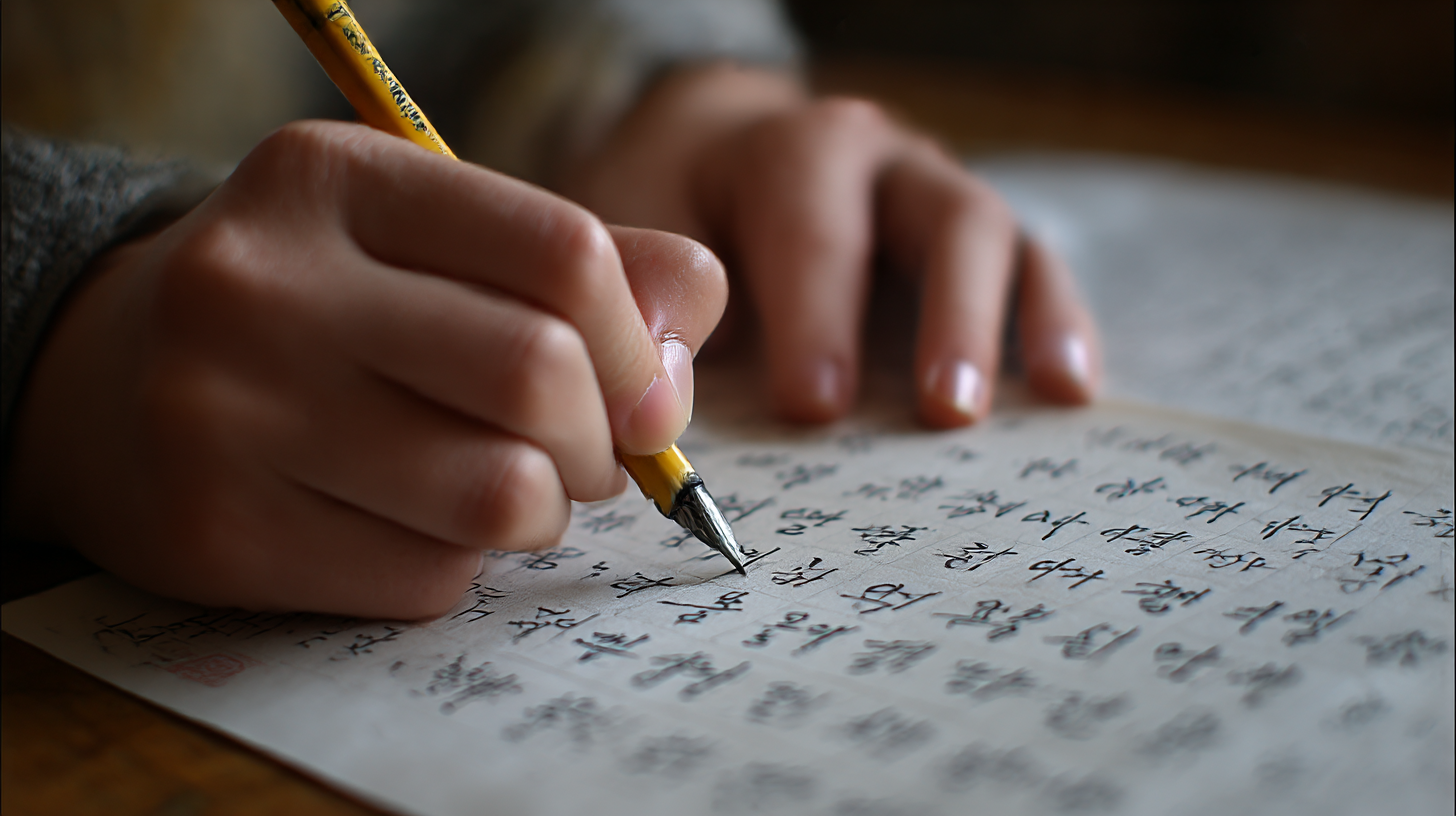
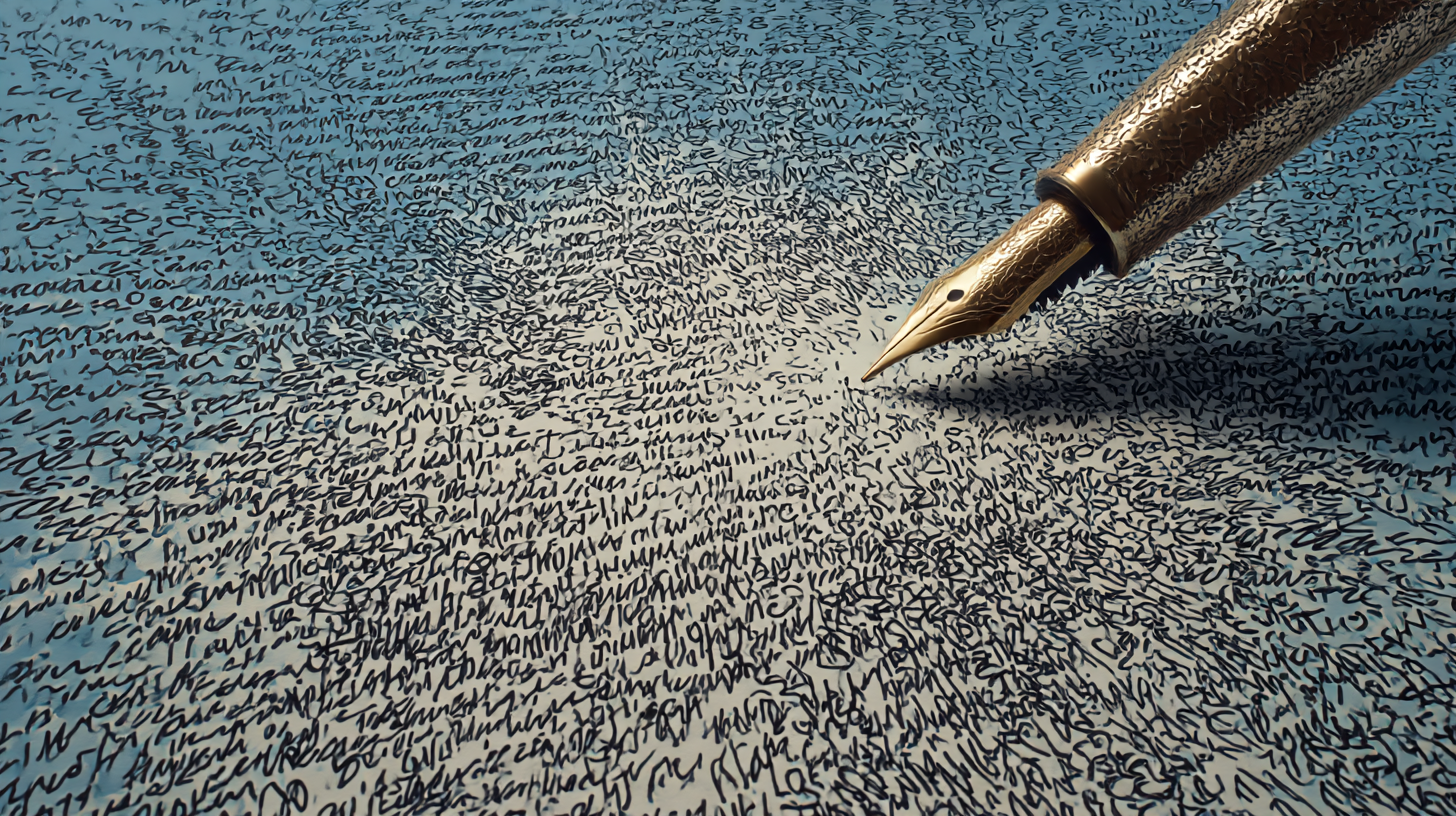
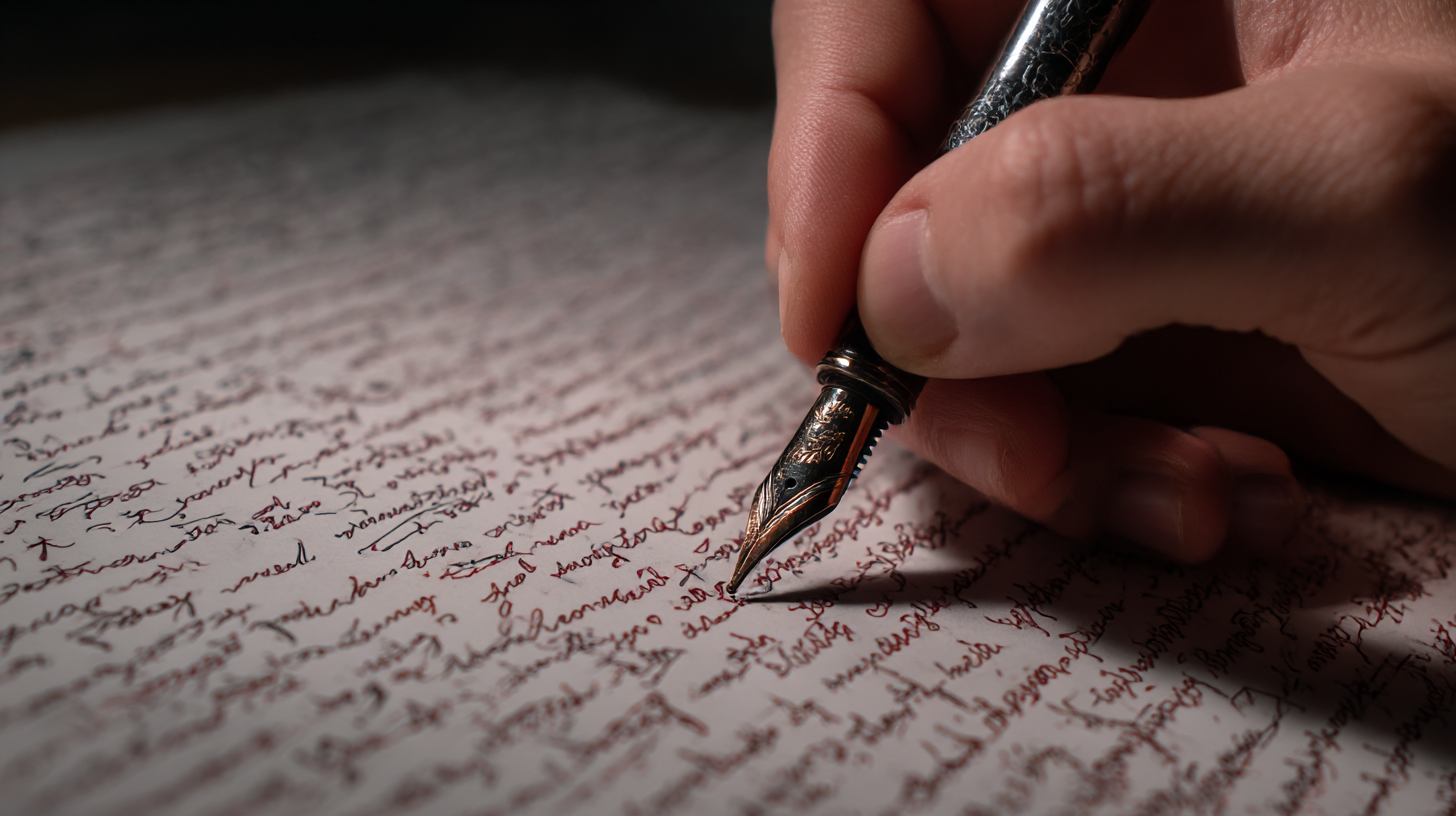
악필 탈출! 바른글씨로 바뀐 전후 비교 실화 ✏ 글씨가 예뻐지고 싶은 마음, 누구나 한 번쯤 품어봤을 거예요. '글씨체도 성격을 드러낸다'는 말처럼, 나를 표현하는 중요한 수단이 글씨랍니다. 하지만 어릴 적부터 악필로 고민했던 사람들은 쉽게 바꾸기 어렵다고 느끼죠.
이번 글에서는 실제로 악필에서 바른 글씨로 바뀐 생생한 사례를 통해 희망을 드려보려고 해요. 방법과 도구, 그리고 변화의 전후까지 낱낱이 알려드릴게요. 2025년, 이제는 글씨로도 인상을 바꾸는 시대랍니다! 😎
많은 사람들이 손글씨를 포기하지만, 꾸준한 연습과 전략만 있다면 누구나 바른글씨로 탈바꿈할 수 있어요. 지금부터 차근차근 소개해드릴게요!
✍ 악필의 원인과 특징
악필은 단순히 글씨가 못생긴 게 아니에요. 대부분 습관이나 자세, 필기 도구의 문제에서 비롯된 경우가 많답니다. 어릴 때부터 펜을 잘못 잡았거나, 조급한 성격으로 빠르게 쓰는 습관이 들면 글씨체가 흐트러지게 돼요.
특히 스마트폰과 컴퓨터에 익숙한 세대는 손글씨를 쓸 기회가 적기 때문에 더 악필이 될 가능성이 커요. 이게 반복되면 손의 근육 기억이 틀어지고, 자음과 모음의 균형이 맞지 않게 되죠. 또 한 가지 원인은 시력이나 집중력 문제예요.
나는 어릴 때부터 줄 없이 낙서하듯 글을 써왔는데, 그게 나중에는 읽기 힘든 글씨체로 굳어져버렸어요. 악필의 원인은 생각보다 단순하지만, 바꾸려면 꽤 많은 의지와 노력이 필요하답니다.
악필은 자신감을 떨어뜨리고, 특히 필기시험이나 메모 전달에서 큰 불이익을 줄 수 있어요. 정리되지 않은 글씨는 머릿속도 정리가 안 된 느낌을 줄 수 있어서, 직장인이나 학생 모두에게 문제로 작용해요.
🧠 악필 주요 원인 비교표
원인 세부 설명 영향 잘못된 펜잡이 손가락 각도가 틀어짐 글씨 모양 왜곡 빠른 필기습관 형태보다 속도를 우선 흘림, 비틀림 현상 디지털 의존 타이핑 위주 생활 손글씨 근육 기억 퇴화 자세 문제 허리, 손목 불균형 글씨가 기울고 삐뚤어짐 이렇게 여러 가지 요인들이 복합적으로 작용해서 악필이 생기는 거예요. 하지만 원인을 알면 그만큼 해결책도 명확해진답니다. 그럼 이제 어떻게 바뀔 수 있었는지 전후 비교 사례를 통해 이어서 알려드릴게요.
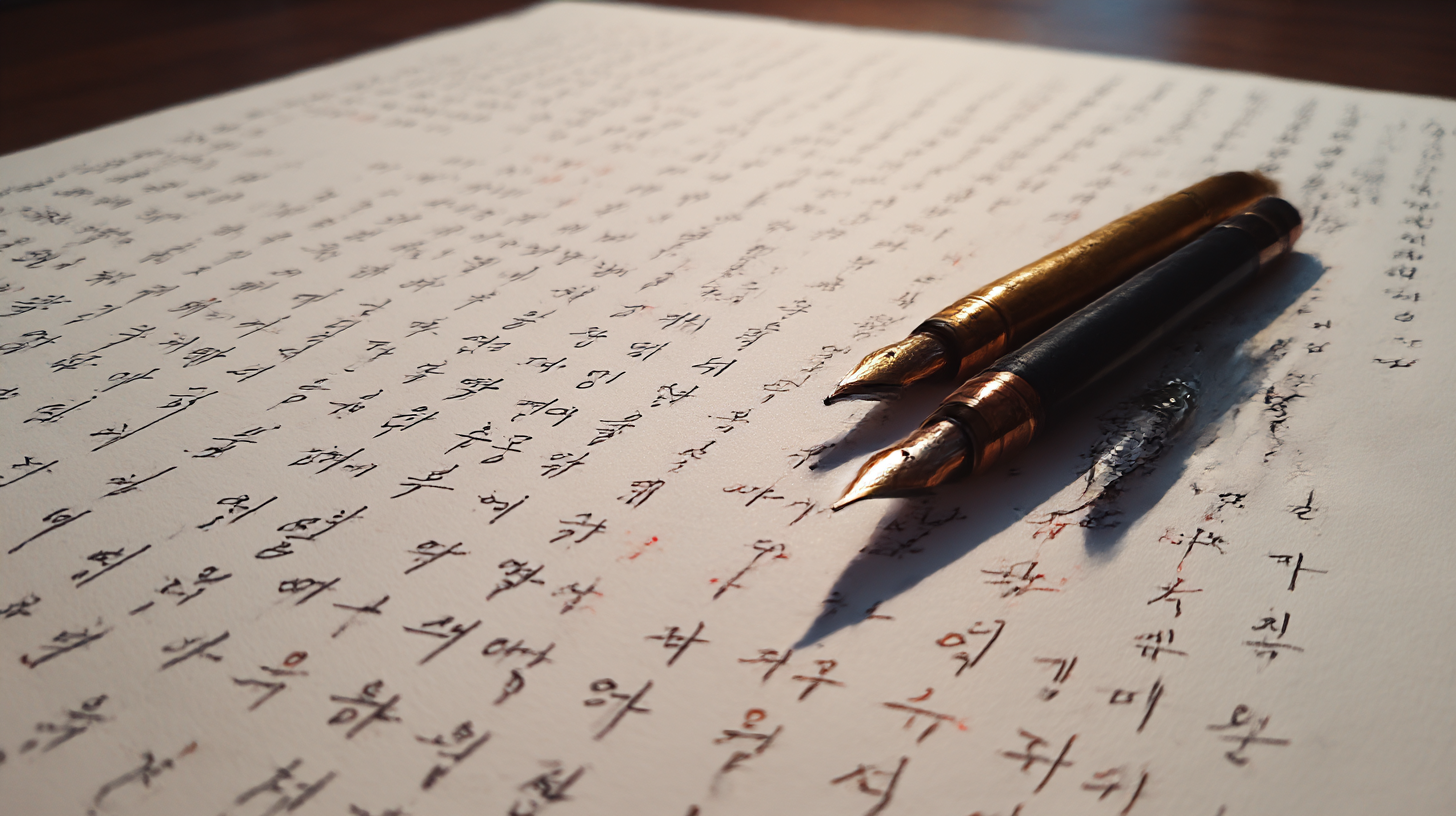
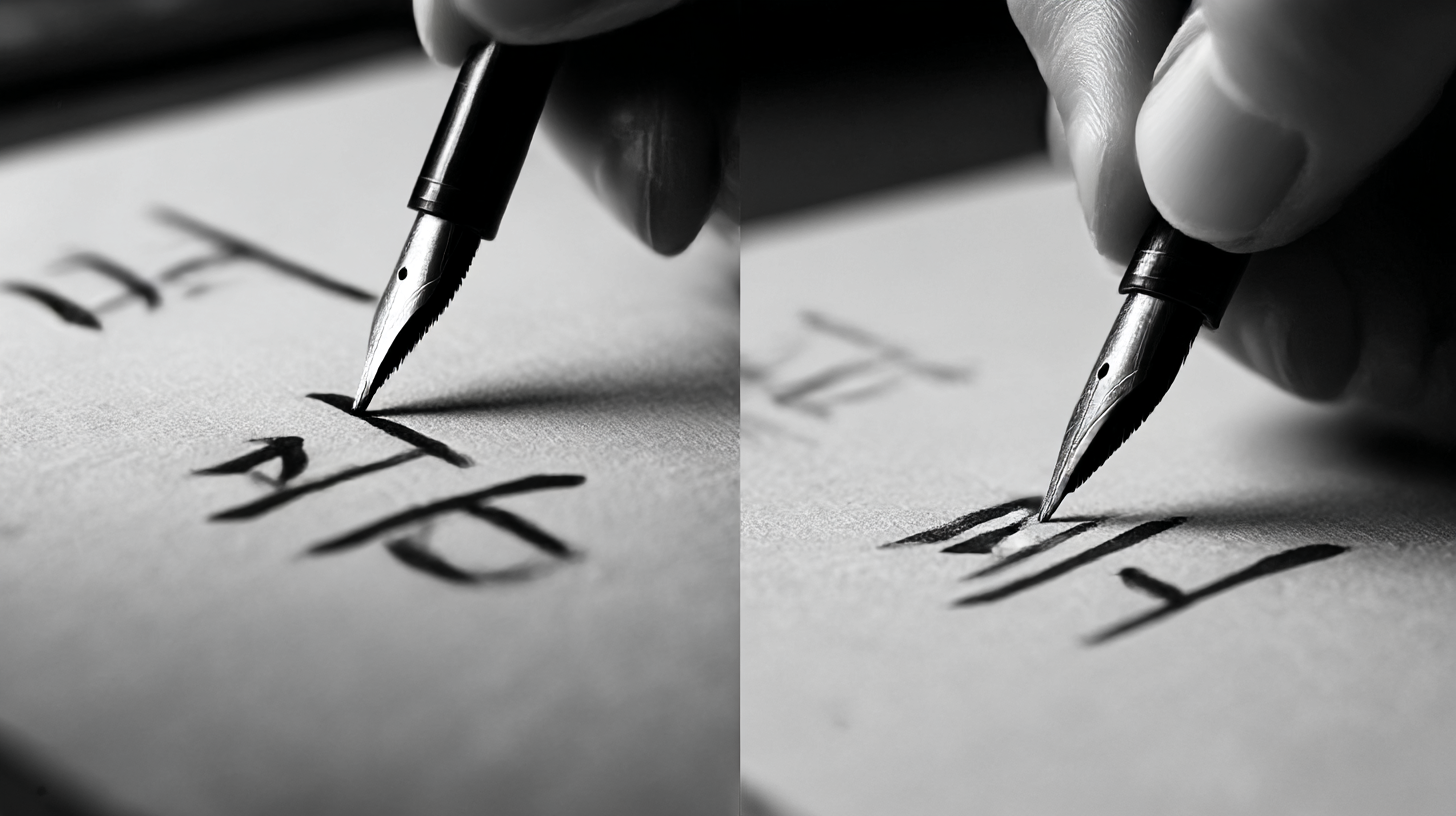
악필의 원인과 특징 ✒ 바른글씨의 효과
글씨가 바뀌면 생각보다 많은 변화가 따라와요. 단순히 예뻐 보이는 것을 넘어서, 자신감, 집중력, 심지어 인간관계에도 긍정적인 영향을 미치게 되죠. 글씨체가 깔끔해지면 메모나 노트를 다시 보기도 좋아지고, 업무나 학습의 효율까지 높아져요.
바른글씨는 보는 사람에게 신뢰감을 주는 힘이 있어요. 손글씨로 쓴 편지, 메모, 카드가 정갈하면 그 마음이 더 잘 전달되는 느낌이 들잖아요? 이건 학교에서든 직장에서든 통하는 부분이에요. 특히 시험이나 면접에서 깔끔한 필기는 은근히 점수를 더 얻게 해주기도 해요.
내가 생각했을 때, 글씨는 말보다 더 많은 걸 말해주는 비언어적 표현 같아요. 정성 들여 쓴 글씨는 그 사람의 태도와 진심을 보여주거든요. 그렇기 때문에 바른 글씨로 바뀐다는 건 단순히 '모양'의 변화가 아닌, 내면의 변화를 의미하기도 해요.
글씨를 바꾸는 과정 자체도 집중력과 인내심을 키우는 훈련이 된답니다. 매일 같은 시간에 꾸준히 연습하면, 자연스럽게 일상의 루틴도 생기고 자기관리가 쉬워지는 거죠. 글씨 하나 바꿨을 뿐인데 삶이 정돈되는 느낌, 정말 신기하죠?
🌟 바른글씨 효과 비교표
분야 변화 내용 긍정적 영향 학습 필기 정리 개선 기억력 & 집중력 상승 업무 보고서, 메모 가독성 상승 신뢰도 및 인상 개선 대인관계 편지, 쪽지 전달력 강화 감동 전달 & 정성 표현 정신건강 규칙적인 연습 루틴 자존감 향상 & 자기관리 이처럼 바른글씨는 단순한 외형의 변화가 아니라 삶의 질을 높여주는 일종의 '생활 습관 교정'이에요. 다음 섹션에서는 구체적으로 악필을 어떻게 바꿀 수 있는지, 효과적인 교정법을 소개할게요.
📐 악필 교정 방법
악필을 교정하는 가장 핵심적인 방법은 '올바른 펜 잡기'와 '기초 획 연습'이에요. 손가락 위치, 손목의 각도, 종이의 방향까지 모두 신경 써야 해요. 손목에 힘을 주지 않고, 손가락 끝이 아닌 팔 전체로 글씨를 쓰는 감각을 익히는 게 중요하답니다.
기초 연습은 'ㅡ', 'ㅣ', 'ㅁ', 'ㅅ' 같은 기본 획을 반복하는 것부터 시작해요. 처음엔 줄 노트나 교정용 워크북을 활용하면 좋고, 그 다음엔 자신만의 글씨체를 만들어가는 과정이 따라오죠. 너무 욕심부리지 말고, 하루에 10~15분 정도만 꾸준히 연습하는 게 핵심이에요.
글씨체 교정 앱이나 유튜브 강의도 큰 도움이 돼요. 요즘은 디지털 펜과 태블릿을 활용해서 획 연습도 가능하니까, 손에 잘 맞는 방식을 선택하면 돼요. 중요한 건 '매일 조금씩' 하는 거예요. 무리하게 긴 시간보단 짧고 집중된 시간이 훨씬 효과적이에요.
또 하나 중요한 건 자신에게 맞는 펜 찾기! 펜촉의 두께, 잉크의 흐름, 손에 쥐었을 때의 무게감이 정말 달라요. 필기감이 좋은 펜을 사용하면 스트레스도 줄고 연습이 더 즐거워져요. 나만의 필기구를 찾는 것도 악필 탈출의 핵심 과정이랍니다.
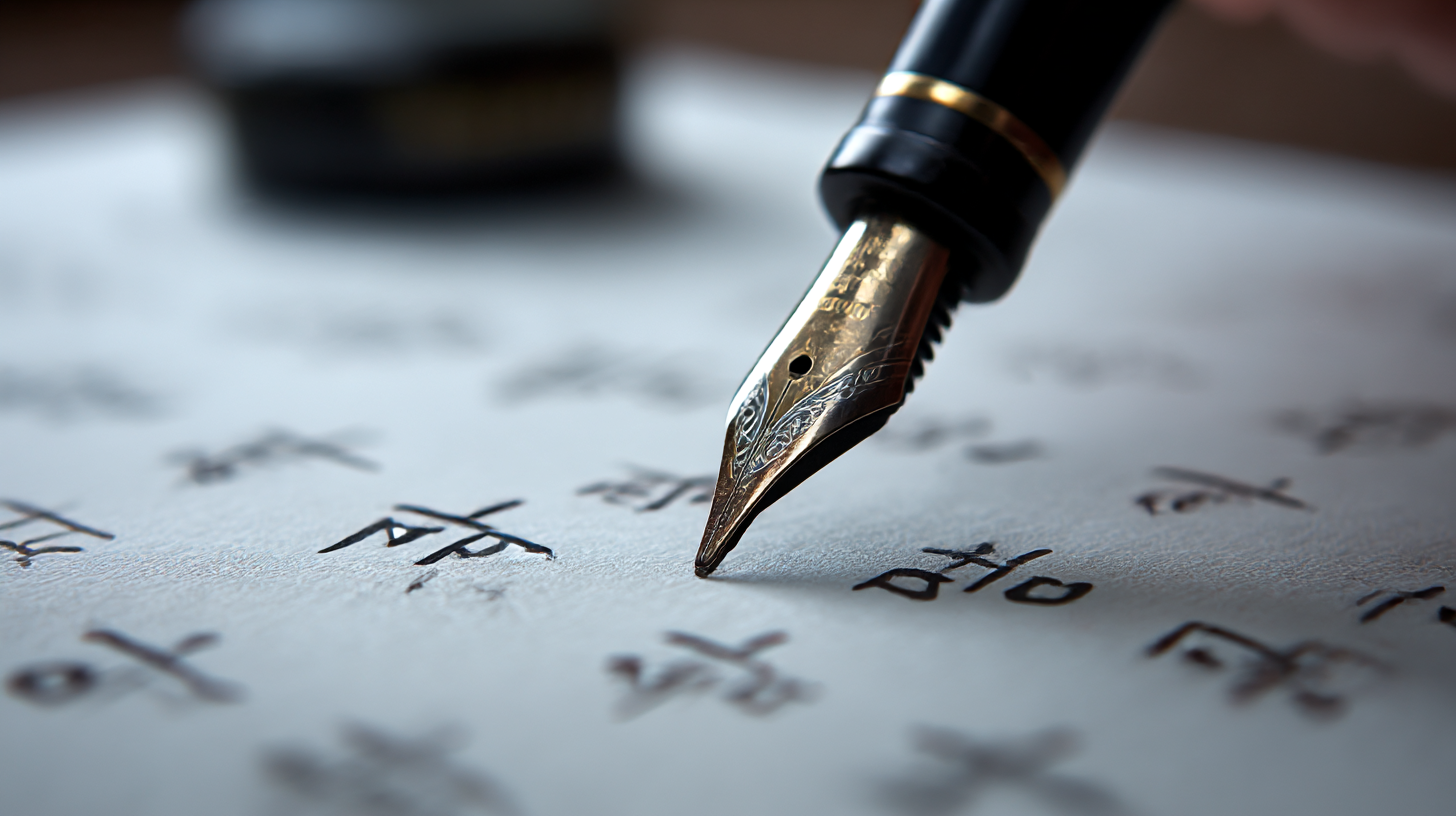
악필 교정 방법 🛠 악필 교정 방법 비교표
방법 핵심 요소 추천 도구 기초 획 반복 획 균형 잡기 교정노트, 모눈종이 펜 그립 교정 정확한 손가락 위치 펜그립 보조기구 글씨체 분석 문자 간격 & 구조 파악 전문가 피드백, 사진 비교 디지털 연습 터치펜 필기 갤럭시탭, 아이패드, 앱 이렇게 다양한 방법 중에서 본인에게 맞는 걸 선택해 천천히 습관화하는 것이 중요해요. 바로 다음 섹션에서는 실제로 악필에서 바른글씨로 바뀐 사람들의 생생한 전후 사진과 이야기를 소개할게요! 기대되죠? 😊
📷 실제 전후 비교 사례
악필에서 바른글씨로 변화한 사람들의 이야기를 보면, 단순히 글씨체만 바뀐 게 아니라 삶 전체가 달라졌다는 걸 느낄 수 있어요. 실력이 늘어가는 글씨를 직접 보면, 동기부여도 되고 나도 할 수 있겠다는 자신감이 생겨요.
예를 들어, 직장인 이민정 씨는 어릴 적부터 갈겨쓴 글씨체 때문에 회의록 작성이나 손편지를 쓸 때마다 민망함을 느꼈대요. 하지만 3개월간 매일 10분씩 악필 교정 워크북을 쓰며 교정한 후, 현재는 문구점의 캘리그래피 강의 요청도 받고 있대요!
또 다른 사례로는 수험생 박준혁 군이 있어요. 급하게 쓰던 필기 습관으로 시험 때 오답 처리도 여러 번 겪었지만, 글씨체를 교정한 뒤 채점 실수도 줄고 필기도 깔끔하게 정리되며 성적까지 올랐다고 해요. 글씨체 변화는 단순히 ‘예쁨’ 이상의 의미를 가져요.
아이를 둔 엄마 김하영 씨는 자녀의 악필이 고민이었는데, 하루 15분씩 함께 연습하며 아이와의 유대감도 높이고, 아이의 자신감도 키워줄 수 있었대요. 글씨 하나로 관계까지 더 좋아진 거죠. 이처럼 전후 비교는 단순한 ‘외형’ 그 이상이에요.
📊 바뀐 글씨체 전후 비교표
이름 교정 전 글씨 특징 교정 후 글씨 변화 소요 기간 이민정 흘림체, 줄 바깥 벗어남 정돈된 명조체 느낌 3개월 박준혁 급하게 쓴 빼곡한 글씨 자간과 행간 정돈 2개월 김하영 일정하지 않은 자모 간격 한눈에 읽히는 정갈함 4개월 이 표처럼, 단순히 '악필에서 벗어났다'는 걸 넘어서 일상 전반에서 긍정적인 변화가 나타나요. 정리된 글씨가 가져오는 효과는 단순한 시각적인 변화보다 훨씬 깊은 만족감을 안겨줘요.
🛠 도움이 되는 교정 도구
악필을 탈출하기 위해선 단순히 연습만으로는 부족할 때가 있어요. 이럴 땐 교정 도구의 도움을 받는 것도 정말 좋아요. 요즘은 펜 하나부터 앱, 전용 워크북까지 다양한 도구들이 나와 있어서, 내 손에 맞는 도구를 고르는 것도 중요한 과정이에요.
먼저 펜은 굵기가 0.38mm~0.5mm인 중성펜이 가장 많이 추천돼요. 너무 얇으면 끊기고, 너무 굵으면 자간이 뭉개지기 쉽거든요. 그리고 펜 그립 보조기구도 많이 써요. 손가락 위치를 자연스럽게 잡아주는 실리콘 고정 도구인데, 처음엔 어색해도 익숙해지면 큰 도움을 준답니다.
워크북은 '글씨 바르게 쓰기' 시리즈나 초등 교정용 글씨노트가 성인들에게도 큰 도움이 돼요. 특히 하루 한 장씩 따라 쓰는 구조로 되어 있어 부담 없이 꾸준히 연습할 수 있어요. 모눈종이도 필수 도구예요. 획의 위치를 눈으로 파악하는 데 아주 효과적이에요.
디지털 도구도 활용해볼 만해요. 아이패드나 갤럭시탭에 스타일러스를 사용해 쓰는 필기 앱들은 글씨를 확대해 분석하기도 좋고, 손의 움직임을 시각적으로 확인할 수 있어요. 특히 굿노트(GoodNotes)나 노트쉘프(Noteshelf) 같은 앱은 교정 템플릿도 제공하죠.
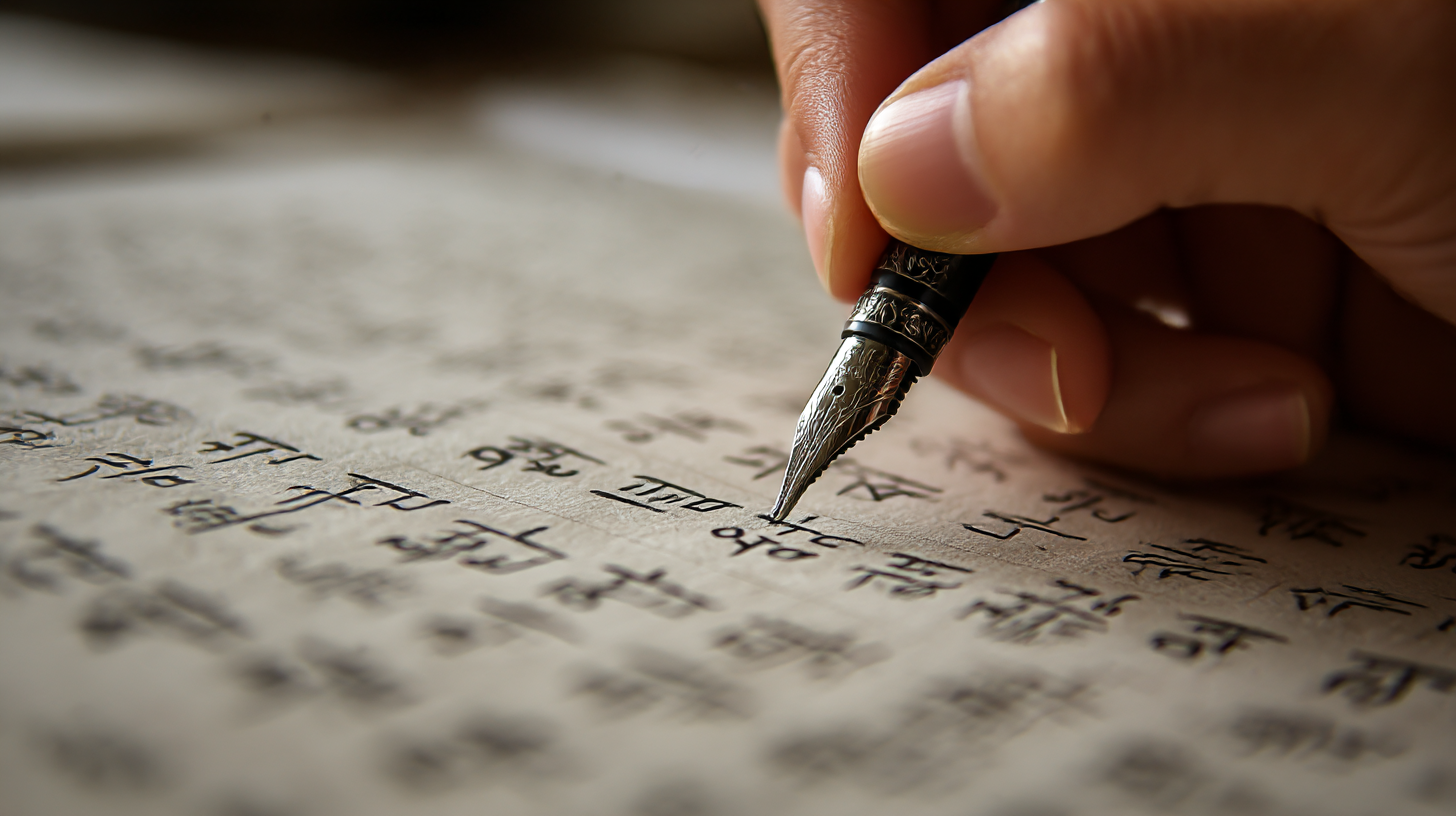
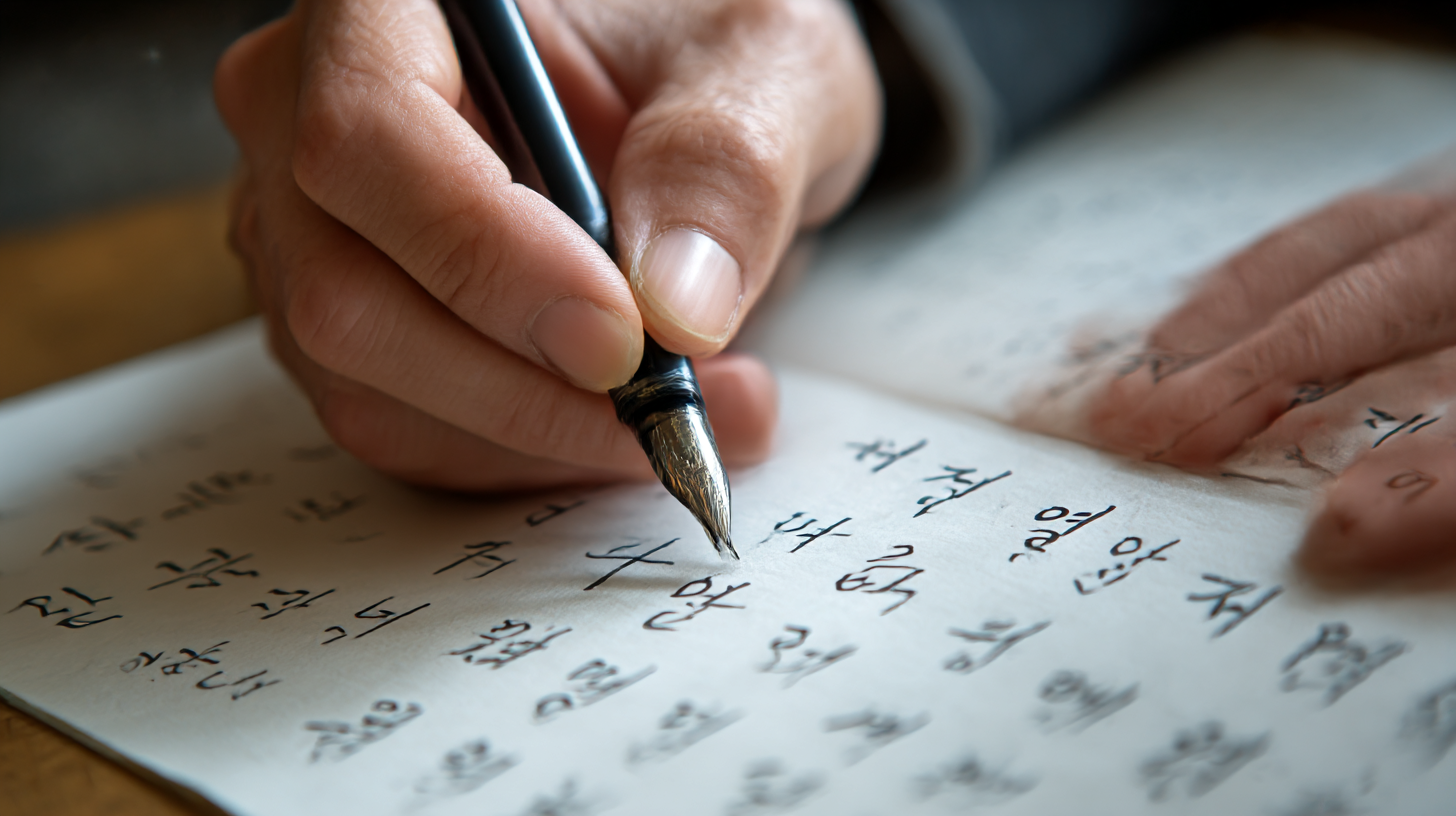
도움이 되는 교정 도구 🖊 추천 교정 도구 비교표
도구 특징 추천 대상 가격대 중성펜 0.4mm 균형 잡힌 필기감 초보자~중급자 1,000~3,000원 펜그립 보조기 손가락 위치 교정 초등~성인 2,000~5,000원 교정 워크북 획 반복 + 정자체 연습 모든 연령 5,000~10,000원 GoodNotes 앱 디지털 필기 교정 태블릿 사용자 10,000원 내외 도구는 어디까지나 보조 수단이에요. 중요한 건 나에게 잘 맞는 걸 찾아내고, 지속적으로 활용하는 거예요. 이제 마지막 실전편! 일상 속에서 글씨 연습을 꾸준히 이어가는 팁을 소개할게요. 📆
📆 꾸준한 연습 루틴
꾸준함은 악필 탈출의 가장 중요한 비결이에요. 하루 10분, 짧은 시간이지만 그 효과는 놀라울 정도로 커요. 중요한 건 매일 같은 시간대에, 같은 장소에서 루틴을 만드는 거예요. 특히 취침 전이나 출근 전, 하루의 루틴에 글씨 연습을 끼워 넣으면 자연스럽게 습관화돼요.
처음엔 간단하게, 날짜나 요일 쓰기부터 시작해보세요. “2025년 5월 25일 월요일”, “오늘의 기분 : 🙂” 같은 글만 써도 연습이 돼요. 그 후엔 좋아하는 책 문장을 필사하거나, 뉴스 기사 일부를 따라 쓰는 것도 좋아요. 너무 무거운 목표는 오히려 부담이 될 수 있거든요.
A2. 물론이에요! 성인이 되어도 꾸준한 연습과 의지만 있다면 얼마든지 교정이 가능해요.
Q3. 하루에 얼마나 연습해야 효과가 있을까요?
A3. 하루 10~15분 정도만 꾸준히 해도 충분해요. 중요한 건 매일 반복하는 습관이에요.
Q4. 디지털 글씨 연습도 효과 있나요?
A4. 네! 태블릿과 스타일러스 펜을 활용한 연습도 손 움직임을 익히는 데 많은 도움이 돼요.
Q5. 펜을 바꾸면 글씨도 바뀌나요?
A5. 어느 정도는 맞아요. 손에 잘 맞는 펜을 쓰면 필기 스트레스가 줄고 글씨체가 안정되기 쉬워요.
Q6. 교정 효과가 나타나기까지 얼마나 걸리나요?
A6. 개인차는 있지만 보통 1~3개월 정도면 눈에 띄는 변화가 나타나요.
Q7. 한글뿐 아니라 영어 글씨도 교정 가능한가요?
A7. 네! 알파벳도 기본 획과 자간 중심으로 연습하면 충분히 예뻐질 수 있어요.
Q8. 아이와 함께 연습하면 도움이 될까요?
A8. 아주 좋아요! 부모와 함께하는 연습은 아이에게 더 좋은 습관과 정서적 안정감을 줄 수 있어요.